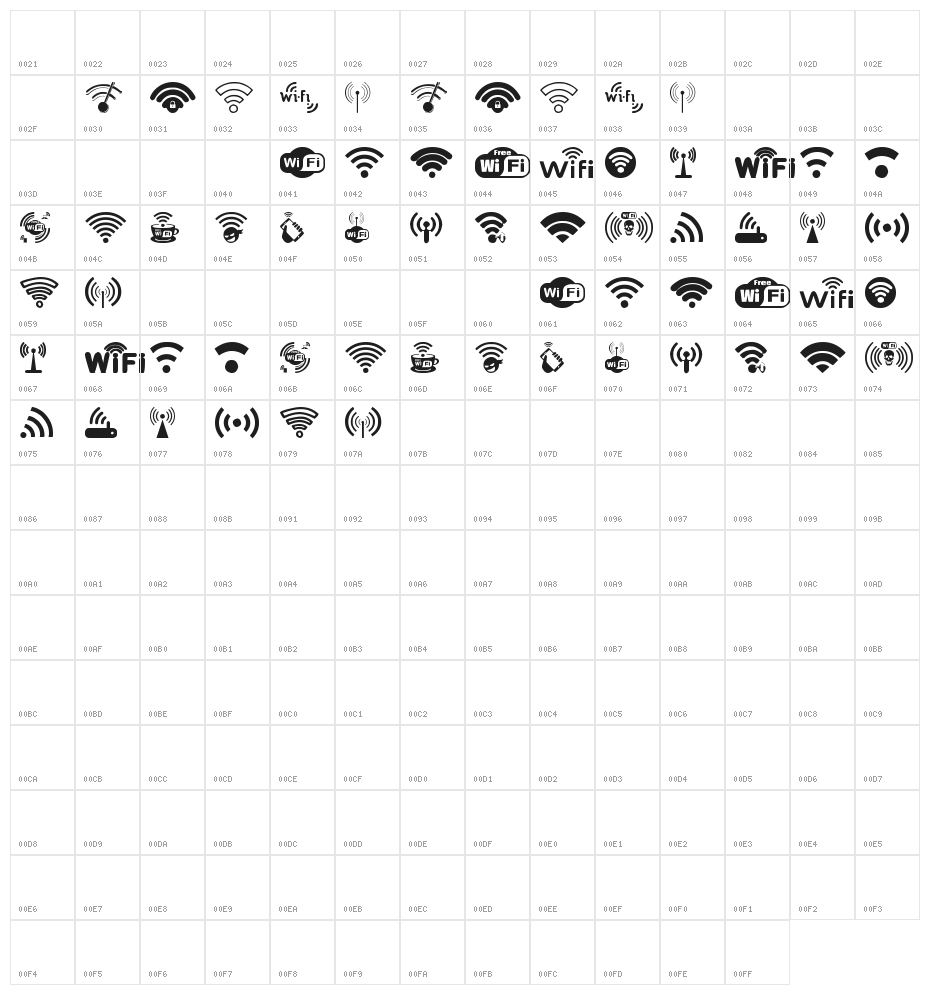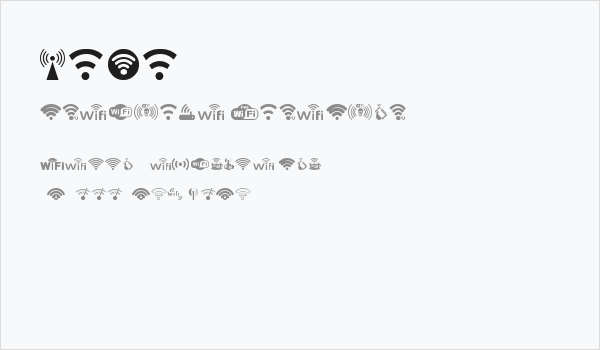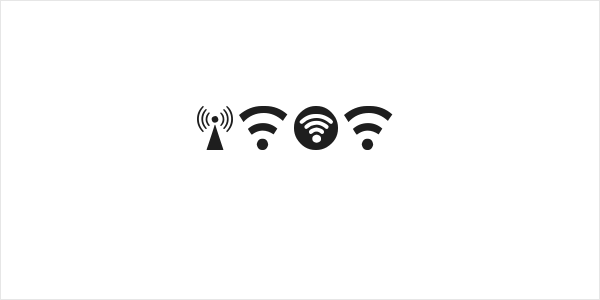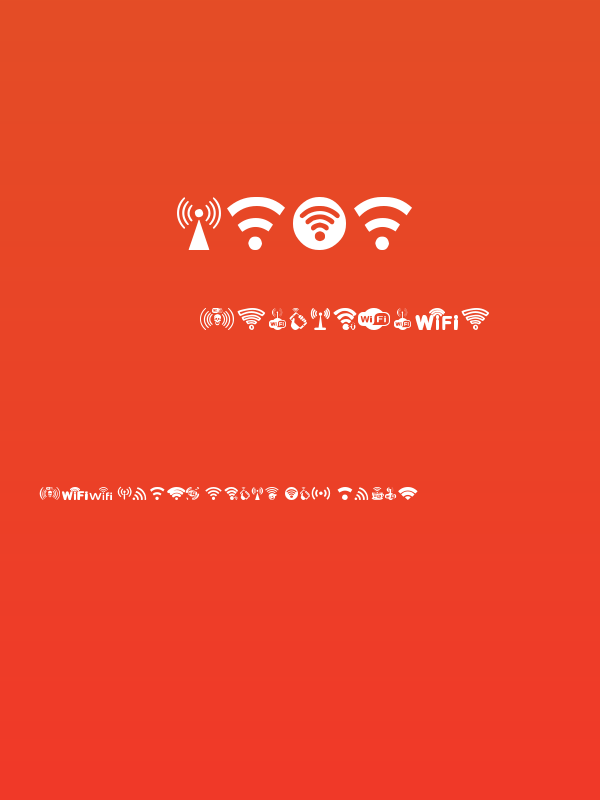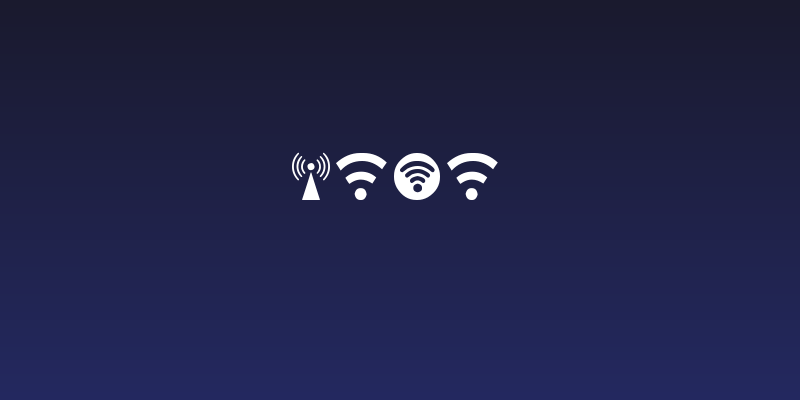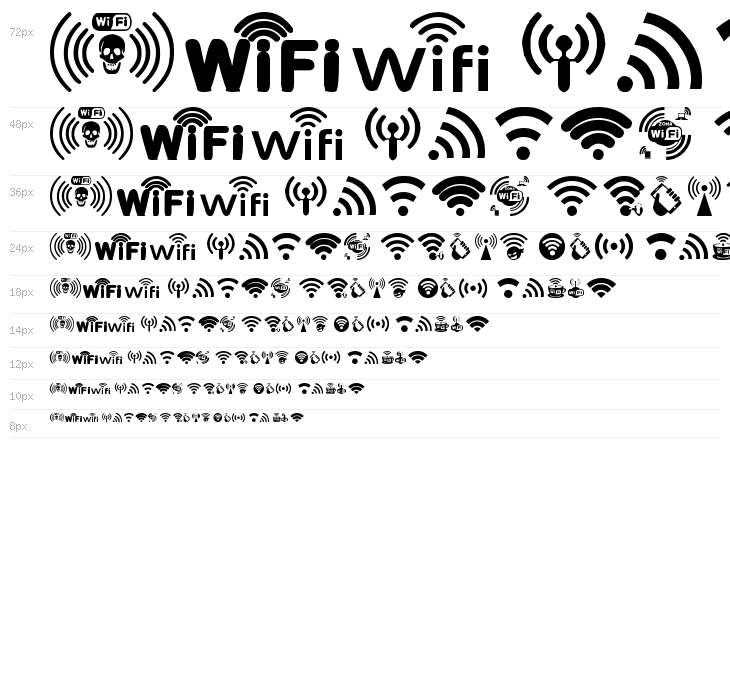
WIFI Font
WIFI MAJUSCULES
WIFI MINUSCULES
WIFI AUTRES CHARS
| Style général | Decorative, Modern, Thematic |
| Cas d'utilisation | Logos, Headlines, Posters, Signage |
| Projets proposés | Tech branding, infographics, signage for wireless zones, digital illustrations, educational materials about connectivity. |